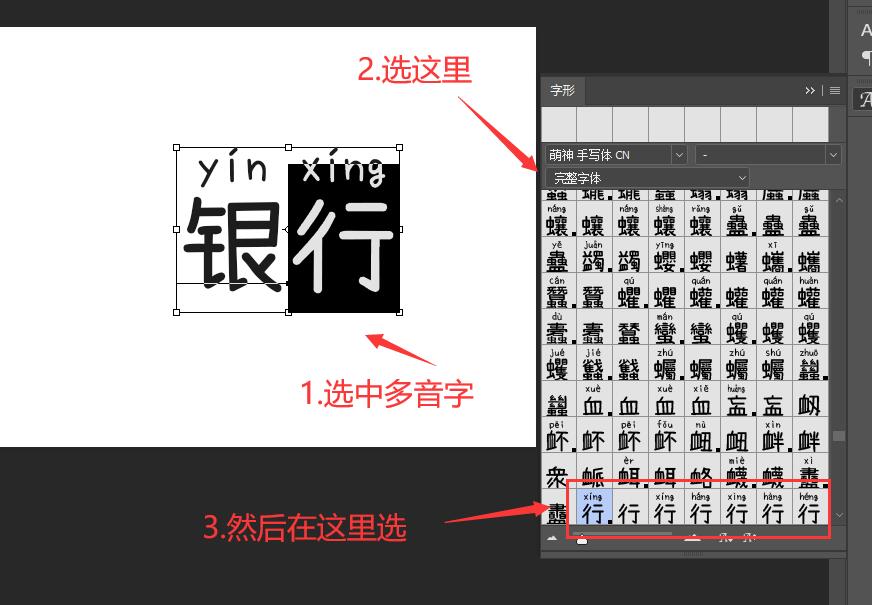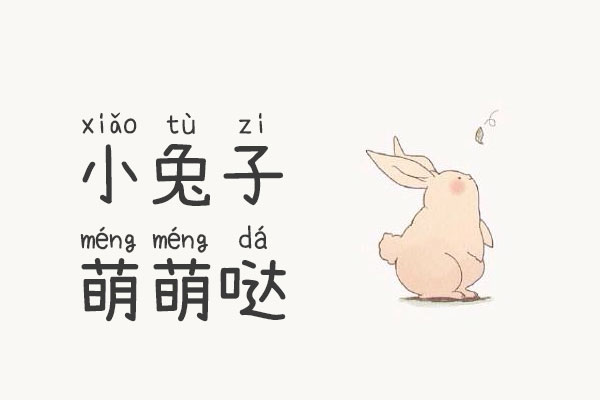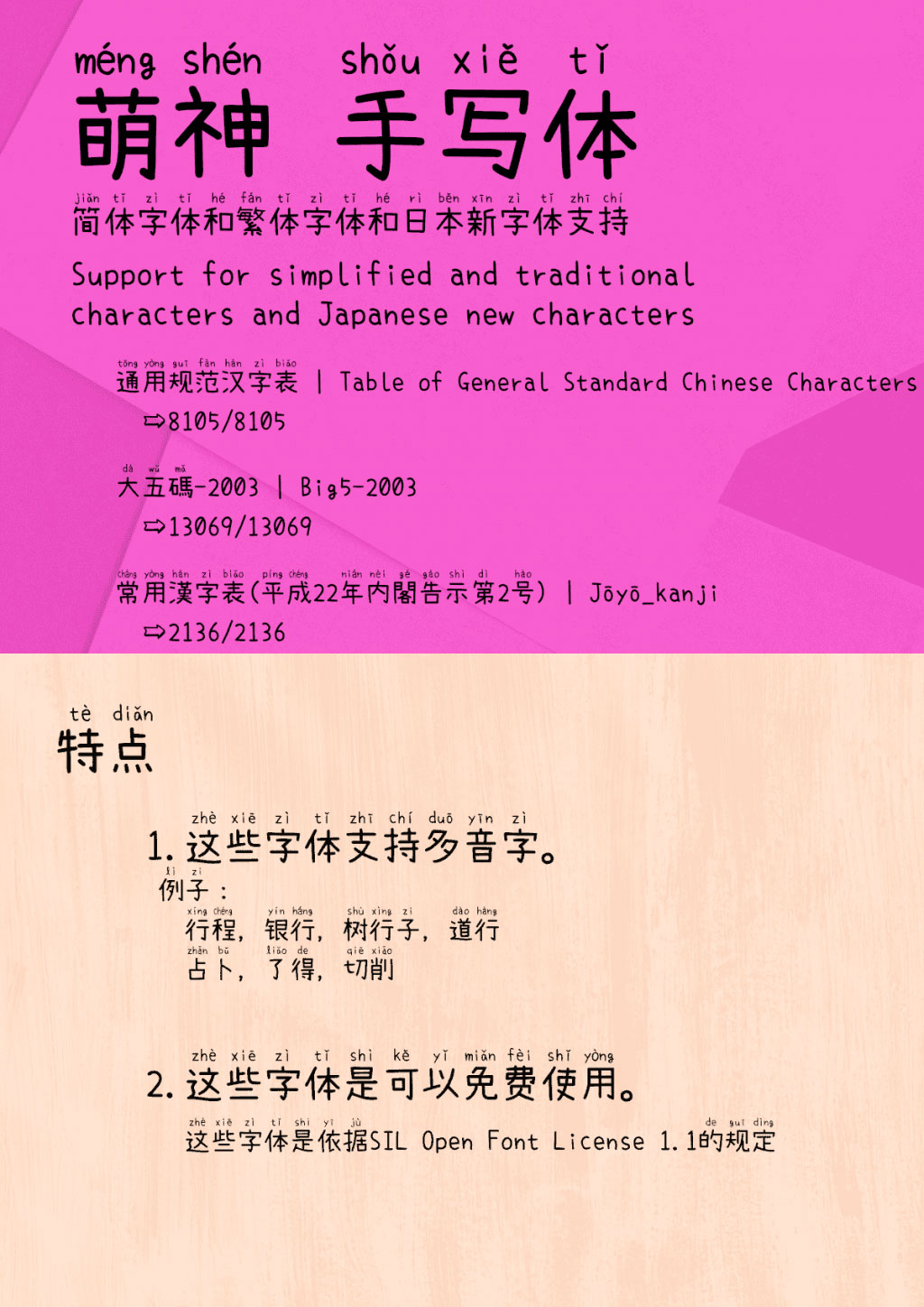
MaruTama是一位日本的网友,他创建了一个名叫萌神项目的网站,专门帮助学生学习中文。萌神手写体是基于已免费开源的小赖字体改造而来的,它是一款可以免费商用的中文字体,还带有拼音标注。这种字体可以帮助学生更快地学习和阅读汉语,它基本上可以显示日语、简体字和繁体字,在简体字和繁体字中加入拼音的字体的制作。
萌神手写体实现了上下文替换功能,以支持多音字。另外,还可以使用Unicode IVS(表意文字变体选择器)来切换到不同的拼音。萌神手写体的字符比较齐全,覆盖了GB2312标准的简体6763字以及繁体国字标准的所有字符,基本不存在缺字现象。萌神手写体是依据SIL Open Font License 1.1授权协议免费公开的,可以免费用于个人及商业用途。如果您想学习中文,萌神手写体绝对是一个不错的选择!